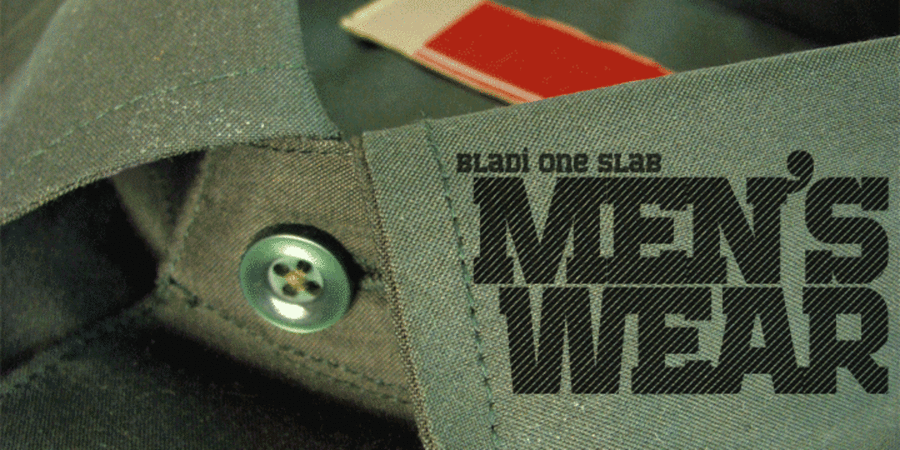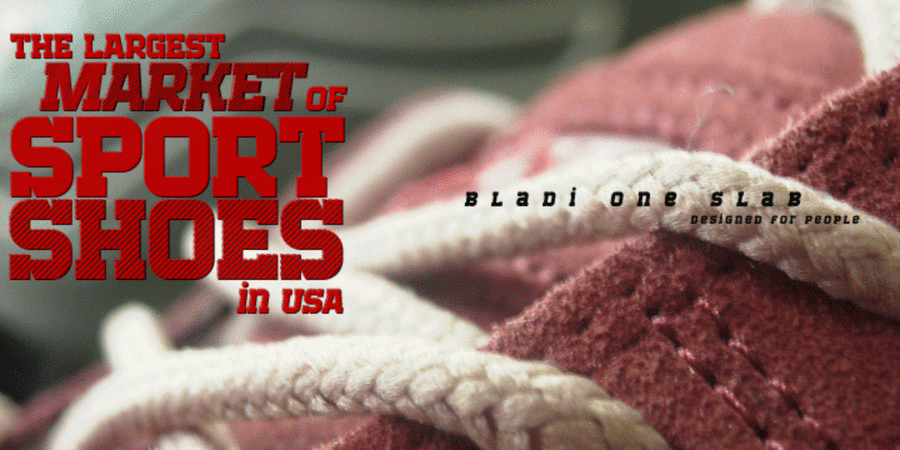
Bladi One Slab 4F (12 fonts)
Самый мужественный брусковый шрифт для заголовков и плакатов. Он настолько суров, что выдерживает прямое попадание противотанковой ракеты. Разработан Сергеем Ткаченко в 2009 году.
Associations for font family Bladi One Slab 4FTypeface personality and character:
strong, powerful, technogenic, heavy, solid, rigid, sharp, steel, industrial, manly, stable, static, robust, formidable, convincing, authoritative, persistent, flat, crisp, high-quality, voiced, rectangular, serious, iron, reliable, self-assured, military, army, soldierly, responsible, severe, square, accurate, logical, automatic, cutting, urban, machine, engineering, urbanistic, rude, loud, durable, daring, important, monumental, totalitarian, workman, motivating, close-fitting, tough, aggressive, railway, ambitious, brutal, game, radical, chopped, incendiary, black, notable, bright, active, splashy, cocky
metallurgy, mechanical engineering, equipment, war, tank, tool, building materials, construction, rock, concrete, machine tool, body-building, fitness equipment, factory, industry, power station, energy industry, jeans, army, repairs, security, protection, airsoft, blockbuster, thriller, action, footwear, constructor, scheme, architecture, engineer, automation, urban studies, city, car, robot, game, weapons, packing, stock, port, box, ammunition, depot, helmet, uniform, railway carriage, machine, Shooter, sport, excavator, SUV, building, mine, miner, rugby, brick, truck, trucker, steel-maker, motor, engine, hardware, technology, railway, workman, cubes, lego, cybersport, Lockdown, computer game, oil, selfie, police, Extreme, stuntman Typeface exhibits stylistic traits: